为宝矿力做设计的字体大师去世了
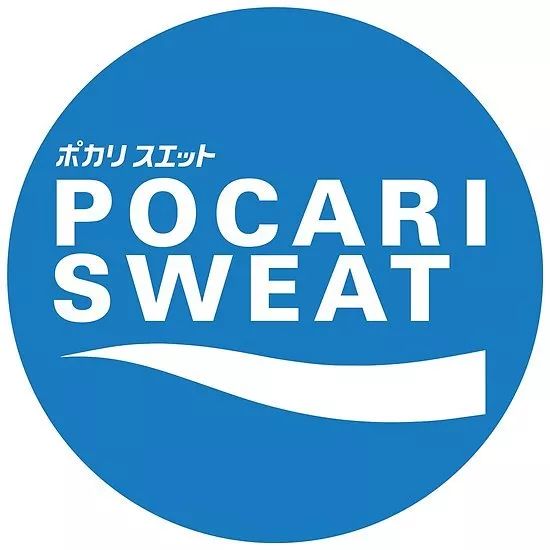
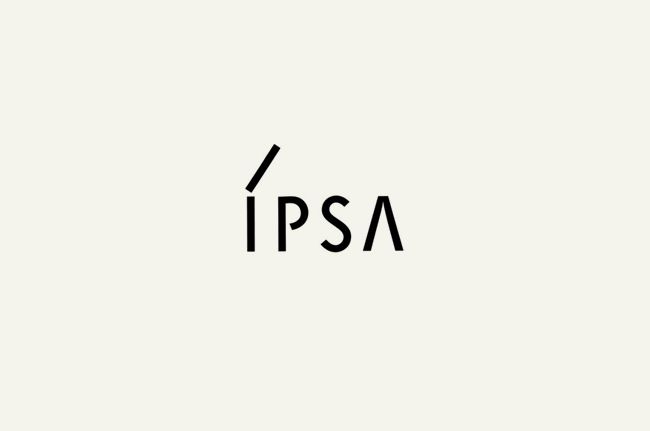
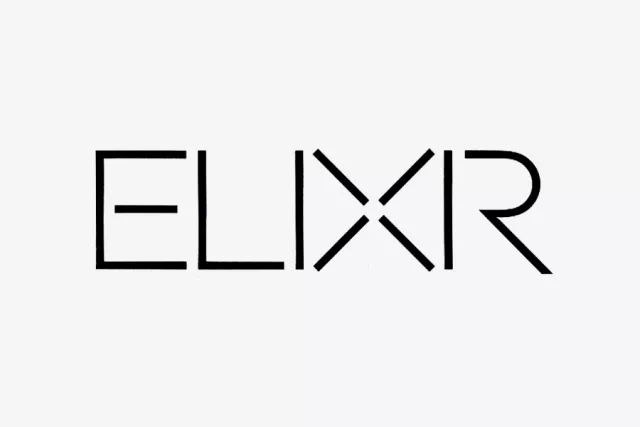
日本运动饮料宝矿力、资生堂旗下化妆品牌IPSA及Elixir、韩国畅销饮料Demisoda……这些我们熟悉的产品的品牌标识其实都是出自同一人之手,他就是德国字体设计师赫尔穆特·施密特(Helmut Schmid)。
令人遗憾的是,当地时间7月2日,赫尔穆特·施密特因急性心力衰竭去世,享年76岁。
施密特1942年生于奥地利,是“瑞士风格字体”的代表人物之一。最开始在德国当排字学徒,上世纪六十年代开始在瑞士巴塞尔设计学院师从艾米尔·鲁德、库尔特·哈尔特和罗伯特·比赫勒,学习字体排印。
艾米尔·鲁德是施密特最尊敬的设计师之一,也是带他走入设计殿堂的精神导师。“鲁德教会我在不停的工作、工作和工作中发掘设计真正的内涵。”
正是在巴塞尔学习的日子里,施密特培养起了自己对字形最初的敏感度。
Emil Ruder, Radikale Liste 1 | 海报设计 1960
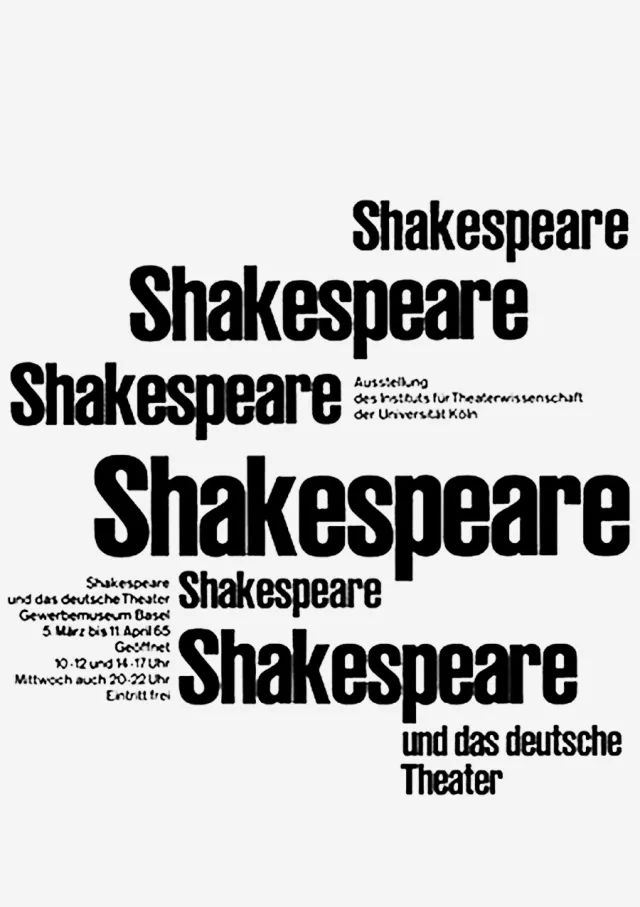
Shakespeare und das deutsche Theater | 海报设计 1964
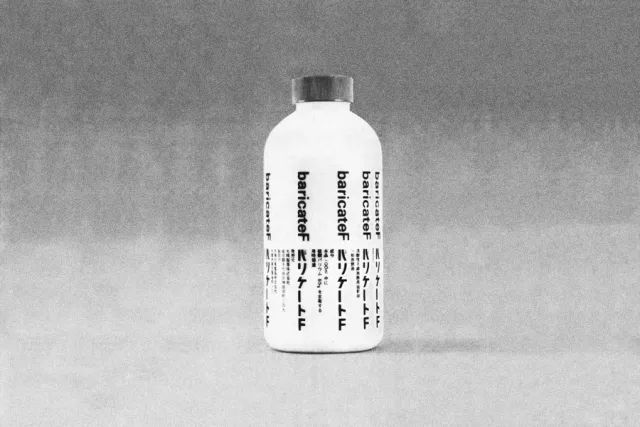
Baricate F | 包装设计 1965
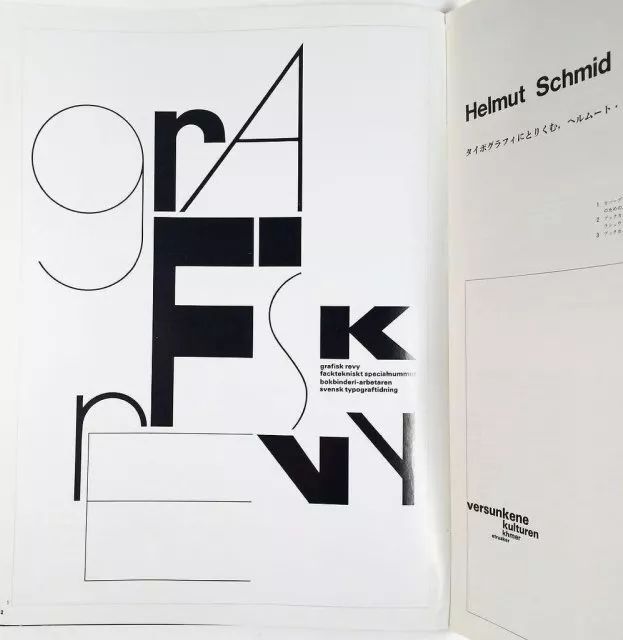
Cover of Grafisk Revy (Scandinavian design journal), 1965
1960年结束了学业后,施密特辗转多个国家工作。先是来到西柏林和斯德哥尔摩,在那里他曾为 Grafisk Revy 设计了封面;然后他搬到了蒙特利尔,就职于Ernst Roch设计公司。
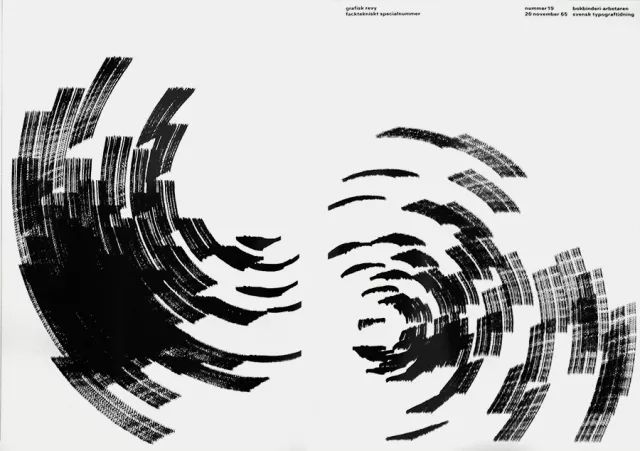
Grafisk Revy n.19 | Magazine 1965
Grafisk Revy n.5 | Magazine 1965
Idea n.78 | Magazine 1966
1973-76的四年间,他在杜塞尔多夫为德国政府工作,负责总理威利勃兰特和赫尔穆特施密特的宣传材料设计,并完成了1976年社会民主党选举标志的设计。
“为德国社民党工作对我而言不仅仅是设计,而是目的性的设计——这意味着我不仅要做出好的设计、赚钱的设计,还要做出有深度内涵的设计。这段经历对我而言荣幸又难忘。”在与DesignCulture的采访中,施密特这样说道。
Die Neue Gesellschaft n.7 Magazine 1974
IDEA n.142 | Magazine 1977
1977年开始,施密特定居于日本大阪,专攻企业设计、编辑设计和产品包装。
在那之后的几年间,施密特拥有了自己的独立设计工作室,完成了为大冢制药(Otsuka Pharmaceutical)旗下药品包装及宝矿力包装的设计。
尽管一直定居在大阪,施密特从不将自己看作是日本设计文化中的一部分,他更喜欢将自己从中分离开来,以一个“外国人”的身份来看待日本设计。
POCARI SWEAT 品牌标识 1980
大冢制药旗下Meptin, Mikelan, Acuatim等药品系列包装,至今仍在使用
Pantocrin | 包装设计 1980
Japan Typography Annual 1985
左:Yarakasukan 广告公司品牌标识 1969
右:Yarakasukan 品牌标识 1995
左:UV white 资生堂旗下化妆品品牌标识
右:Because 资生堂旗下男士化妆品品牌标识
Fibe - Mini 品牌标识设计
1988年,施密特加入了 AGI 及 Atypl (国际字体排印协会),他的作品也开始在日本及荷兰等地展出。
施密特同样热心于设计教育。2000-12年间,施密特在神户设计大学担任讲师,教授字体排印,并在首尔弘益大学担任过一年全职教授。除此之外,他还曾在中国、德国、印度、日本、韩国、新加坡和瑞士等多个国家开展设计讲座。
Design is attitude 展览海报 2007
新加坡南洋理工大学艺术与设计学院
Design is attitude 展览海报 2011
施密特是许多国际知名设计杂志如瑞士《TM》、日本《IDEA》、英国《Baseline》的供稿人,曾撰写过大量关于排版的文章和论文。
1980年,施密特编辑的《今日文字设计 (Typography Today)》作为《Idea》的特刊出版,接着在1981年以书籍形式由日本诚文堂新光社再版,书中收录了15个国家88位设计师的作品,展现了现代文字设计的面貌。2007年该书经过扩编后由中国青年出版社再版。
「今日文字设计」1980
「 Japan Japanese 」2012
Typography Reflections no.7
1989年,他开始出版名为“设计思考(Typography Reflections)”的一系列书籍。
1997年,他在日本朗文堂出版了96页的《通往巴塞尔之路》,以缅怀他年轻时的导师。
2006年,由施密特撰写,HFD Duesseldorf的Fjodor Geijko 编辑和设计的《helmut schmid: design is attitude》由巴塞尔出版。
IDEA n.333 2009年3月刊
2009年,他还为《IDEA》第333期刊“Ruder typography Ruder Phlosophy”进行了编撰和设计,在这本220页的特刊里,收录和剖析了瑞士平面设计大师艾米尔·鲁德的设计作品。
Design360° no.51 | 设计师字库 2014.06
2014年,Design360°杂志第51期中,我们有幸邀请到施密特为读者推荐了一款字体——Univers。
施密特在采访中说,“我经常使用这款字体,不是因为它现在、过去或者未来十分流行,而是因为它是一款舒适和易读的字形。通过不断运用Univers,我相信我能更加了解字体,因为我能与字体保持一个持续的对话。”